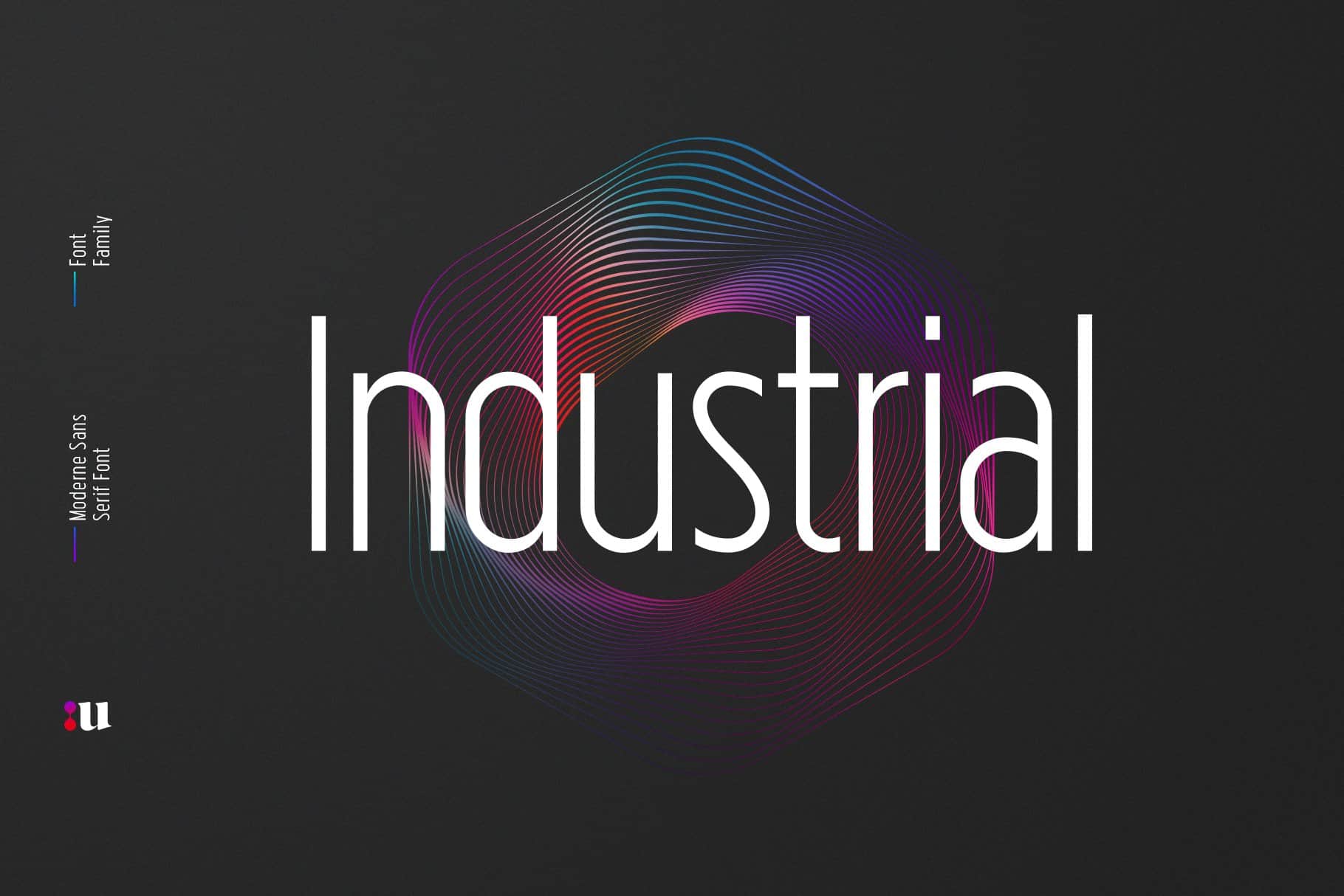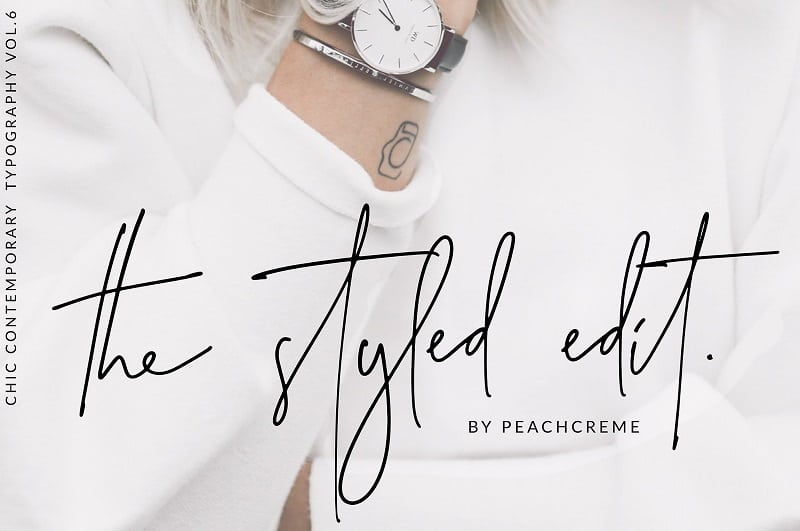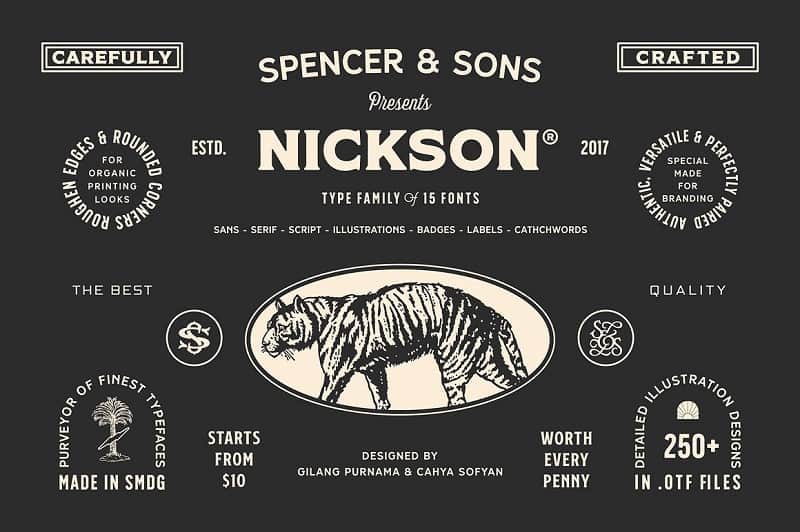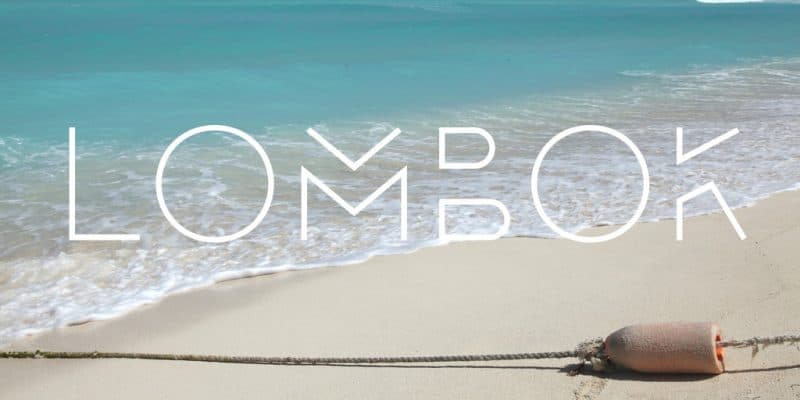
33 лучших шрифта пользовательского интерфейса, которые придадут вашему дизайну потрясающий вид (2021 г.)
Опубликовано: 2021-09-26Что делает дизайн пользовательского интерфейса потрясающим? Некоторые из вас могут сказать простота, или, может быть, выравнивание или, может быть, пустое пространство. И могут быть люди, которые могут вообще исключить эту концепцию.
Если вы спросите меня, я бы сказал, что это типографика, не удивляйтесь. Шрифты — неотъемлемый элемент любого дизайна, они могут изменить внешний вид любого сайта и сделать ваш графический дизайн стильным и инновационным. Использование премиальных и стильных шрифтов может оказать огромное влияние на вашу аудиторию.
Тем не менее, вы должны знать, что веб-шрифты способны даже много раз искажать вашу визуализацию. Возможно, в разных браузерах они отображаются по-разному.
Поскольку мы здесь, чтобы помочь вам в этой статье, мы порекомендуем серию шрифтов, которые технически и визуально удобны для чтения и совместимы с различными браузерами и ОС.
Давайте прыгнем в это…
Шрифт низкого заряда батареи — забавный шрифт для дисплея
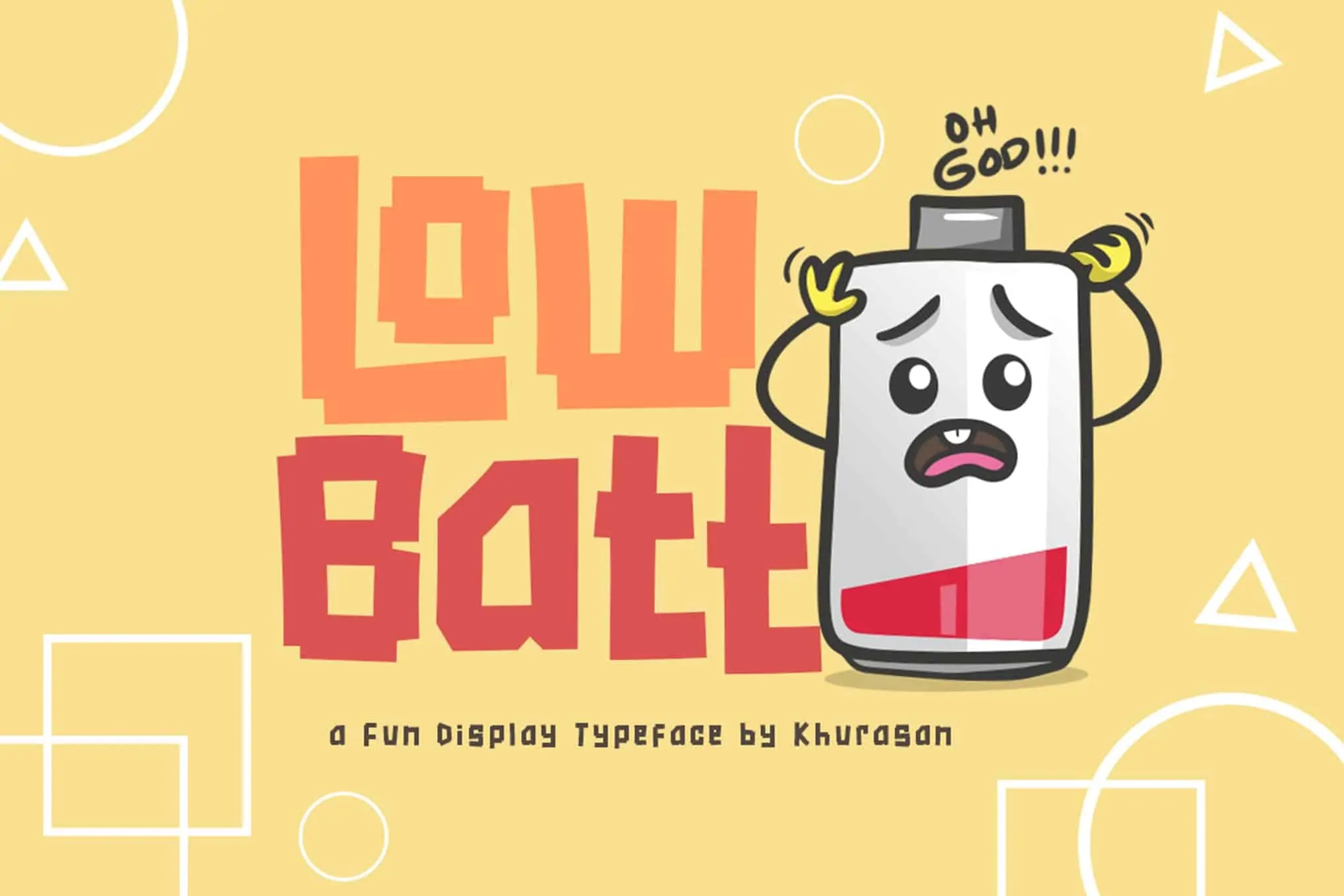
Низкий уровень заряда батареи — это забавный причудливый блочный шрифт, который идеально подходит для логотипов или заголовков. Он имеет неровные края и прямые линии, что придает ему графическое ощущение. Этот шрифт был бы идеальным для технических текстов или для дисплеев, которые очень привлекают внимание.
Berlin Rounded Font — Sans Serif / Display Typeface — один из ЛУЧШИХ ШРИФТОВ UI 2020
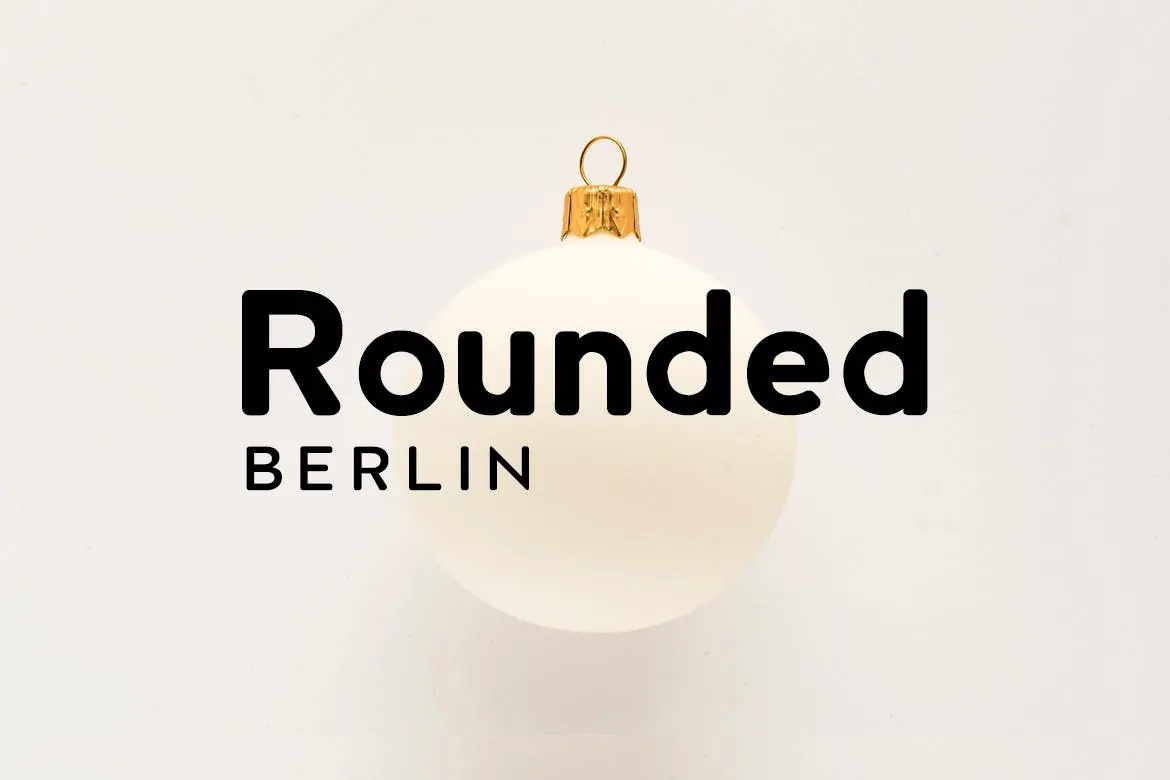
Шрифт Berlin Rounded — это разновидность популярного шрифта пользовательского интерфейса. Он имеет чистый вид, который легко читается. Он идеально подходит для текстов, заголовков или дисплеев. Классический шрифт имеет большое значение, и этот поможет сохранить ваши проекты в тонусе.
Bw Surco — семейство шрифтов
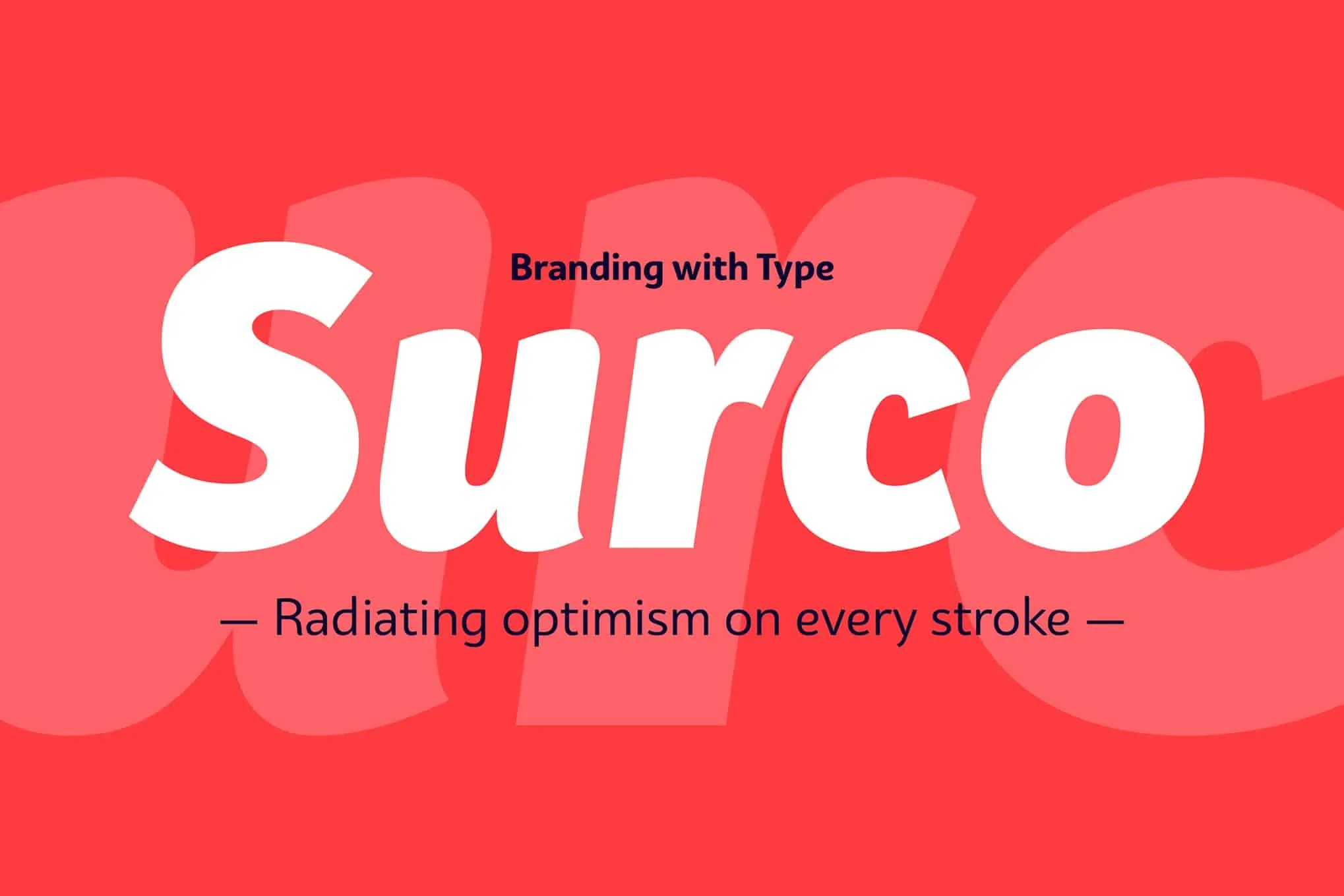
BW Surco — необычный шрифт, который выглядит как рукописный с графическими элементами. Он имеет изогнутые края и удлиненную форму, чтобы добавить элегантности этому забавному типу принта. Это хороший шрифт для использования в рекламных целях, которые привлекают внимание.
Articulat CF — семейство модернистских шрифтов без засечек — ЛУЧШИЕ ШРИФТЫ UI 2020
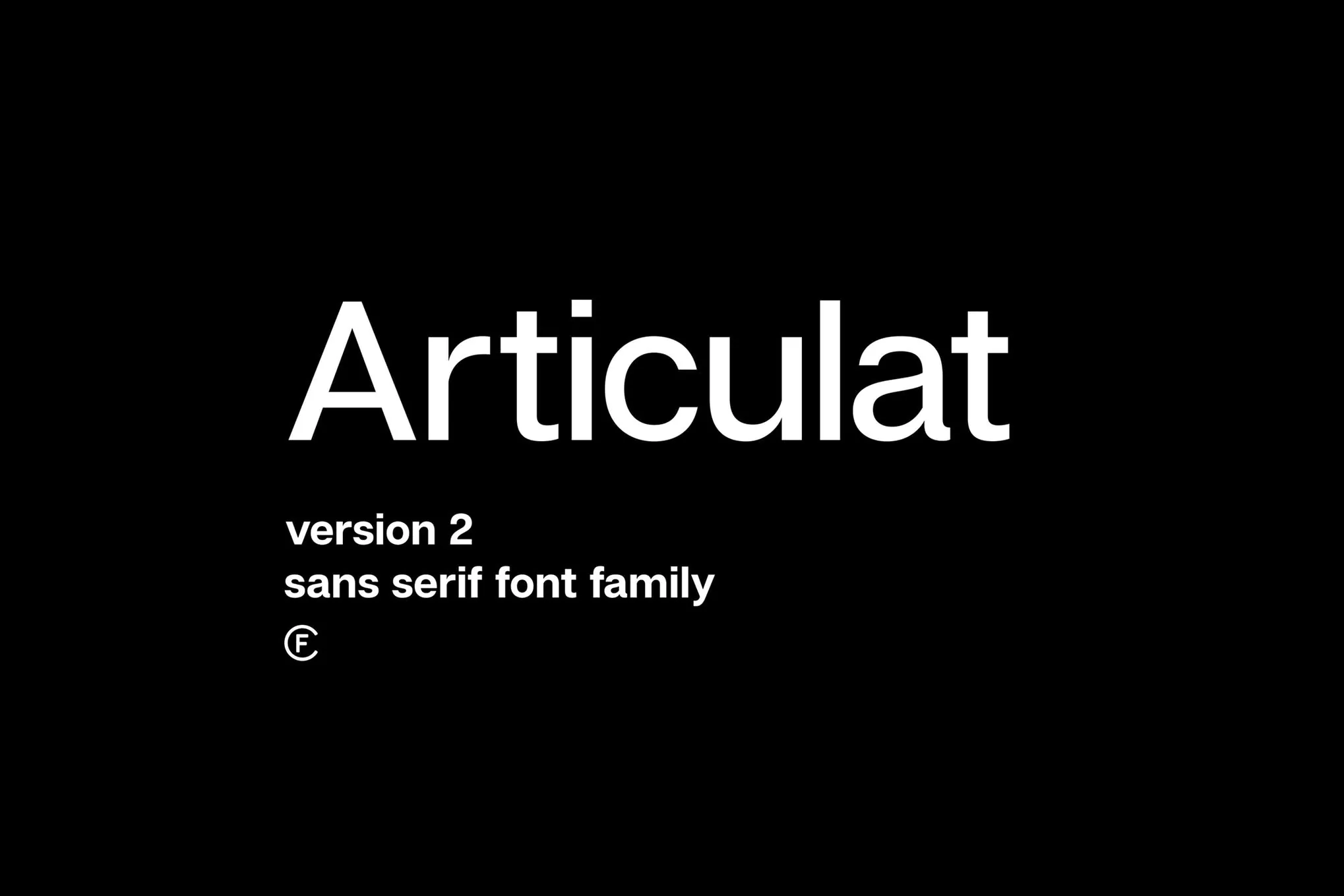
Articulate является частью стиля шрифта Sans Serif с его минимальным внешним видом. Он так же хорошо округлен и продуман, как и слова, которые он будет представлять. Ищете свежий взгляд на современный шрифт? Articulat можно легко использовать практически для любого проекта благодаря своей универсальности.
Шрифт Gelion UI — шрифт Geometrick Grotesk без засечек
Gelion — смелый, молодежный и современный шрифт пользовательского интерфейса 2020 года. Это тот шрифт, который вы хотите использовать, когда разговариваете с молодым клиентом, который все еще принимает решения о своих покупках, которому нужна информация и который хочет чувствовать себя они являются частью семьи сайта.
Вы приветствуете людей на сайте с этим шрифтом, потому что он не имеет никаких излишеств. Кроме того, этот шрифт достаточно полный, чтобы его мог прочитать любой. Вы можете изменить шрифт на любой размер, и он все равно будет четким. У вас как у дизайнера гораздо больше гибкости при использовании этого шрифта.
Банковский шрифт — яркий современный тип отображения пользовательского интерфейса
Вы можете описать Bank Typeface всего одним словом, и это слово — дурь. Это шрифт с заглавными буквами, разработанный для современных приложений, его стиль уникален и заставляет вас затаить дыхание. Он имеет 2 стиля: с подкладкой и с секциями, один из которых был разработан для наложения друг на друга, чтобы создать альтернативный великолепный третий стиль.
Все смешанное вместе выглядит совершенно потрясающе и футуристично. Банк идеально подходит для брендинга проектов и редизайна веб-сайтов, чтобы оказывать влияние и производить впечатление на зрителя.
Norsemen — лучший шрифт ручной работы 2020
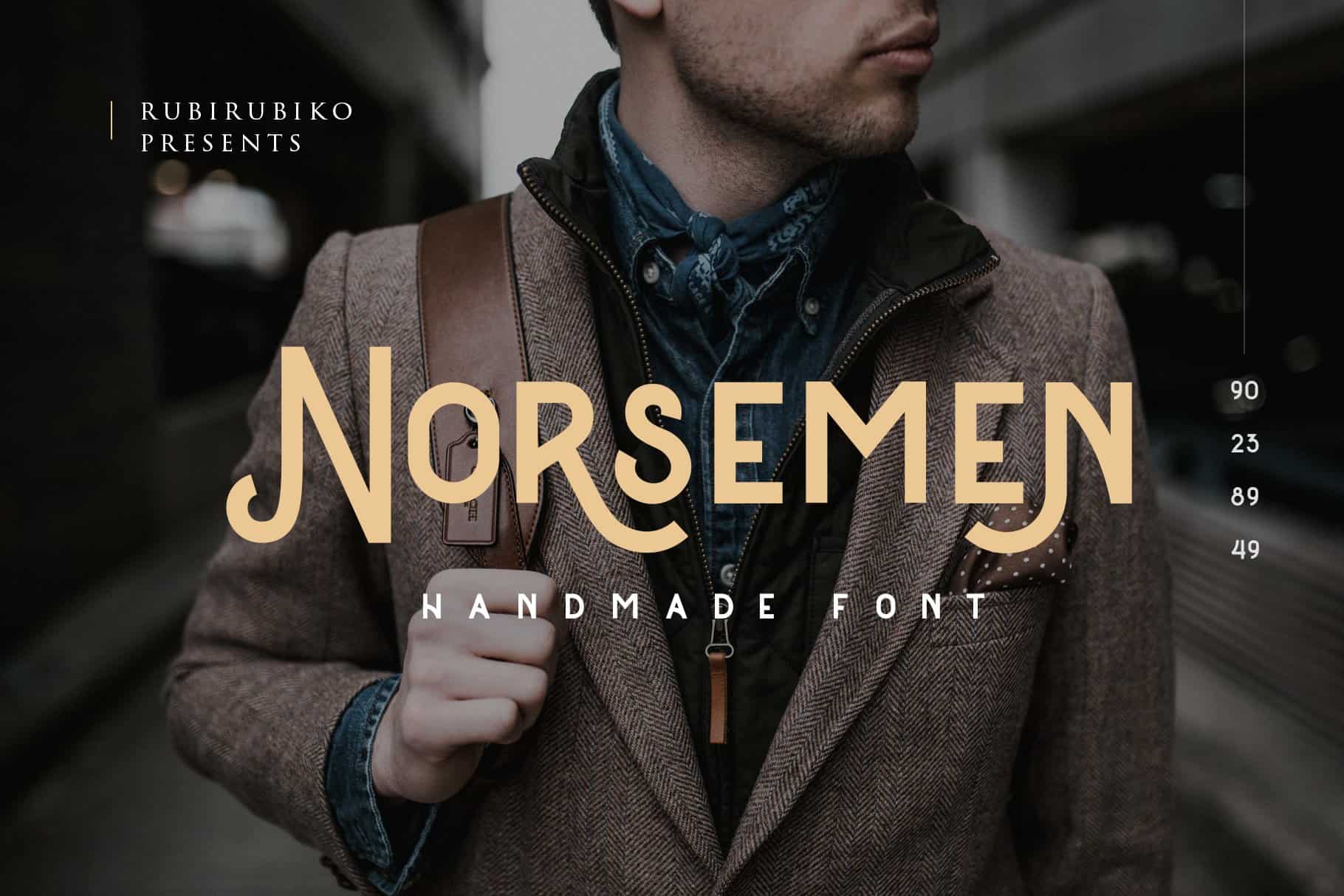
Шрифт Norsemen выглядит так, как описано. Вы смотрите на шрифт, который, кажется, был написан от руки кем-то, кто работал у берегов Норвегии и путешествовал через Атлантику в поисках Гренландии.
Стиль немного более неформальный, чем другие шрифты, и он может хорошо работать на игровой платформе или на сайте, где молодые люди получают информацию или покупают. Из-за грубого характера шрифта его может быть удобно использовать для открытия вашего приложения или веб-сайта, и вы можете смешивать другие шрифты на сайте для таких вещей, как статьи или описания продуктов.
Visby Slab — современный шрифт
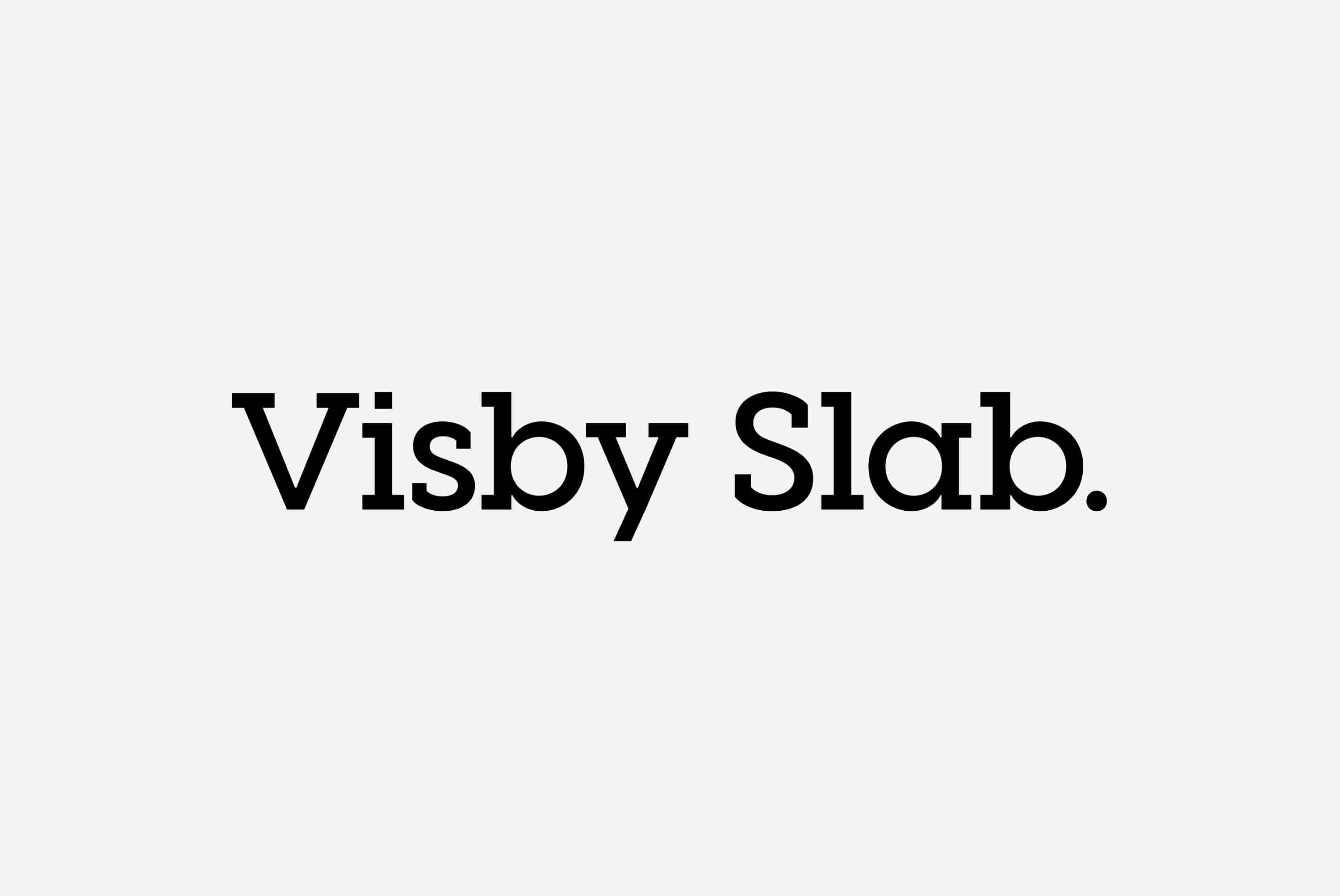
Visby Slab — это шрифт, который выглядит так, как будто он пришел из современной пишущей машинки. Это комплимент высшего порядка, потому что вы можете представить, как этот шрифт анимируется, когда он печатает приветствие в дизайне вашего пользовательского интерфейса.
Вы можете использовать этот шрифт, когда хотите представить себя авторитетом в своей области. Вы можете сделать так, чтобы ваш бизнес выглядел так, будто в нем работают лицензированные профессионалы, работающие в вашей отрасли. Кроме того, этот шрифт хорошо работает в информационных статьях, биографиях сотрудников и описаниях услуг.
Вывод
Вы можете без проблем добавить свежий вид своему проекту, используя эти лучшие шрифты пользовательского интерфейса. Протестируйте их все, прежде чем принять окончательное решение и опубликовать в Интернете.